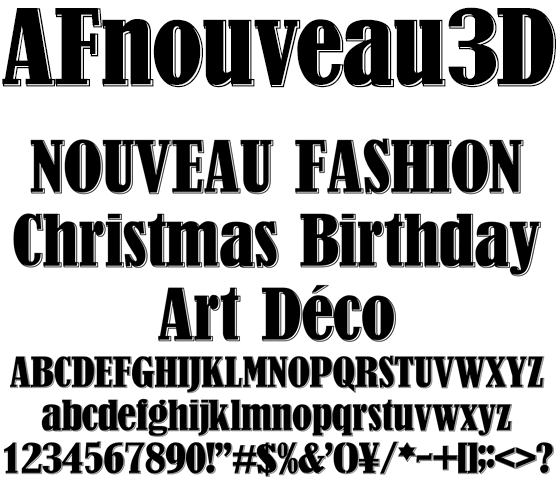
アールデコ調な欧文 AFnouveau3D
AFnouveau3D
アールデコ調なファッション系ドキュメント、バースデー、クリスマスなどのイベントドキュメントに最適なお洒落な欧文フォント。立体感あるデザインが重みを醸し出します。動画テロップ、Web Server へのアップロード、フォント共有サーバー利用、PDF エンベッド、印刷やロゴなど作成と登録、印影や彫刻、画像化後ソフトへのバンドルなど商用利用できます。